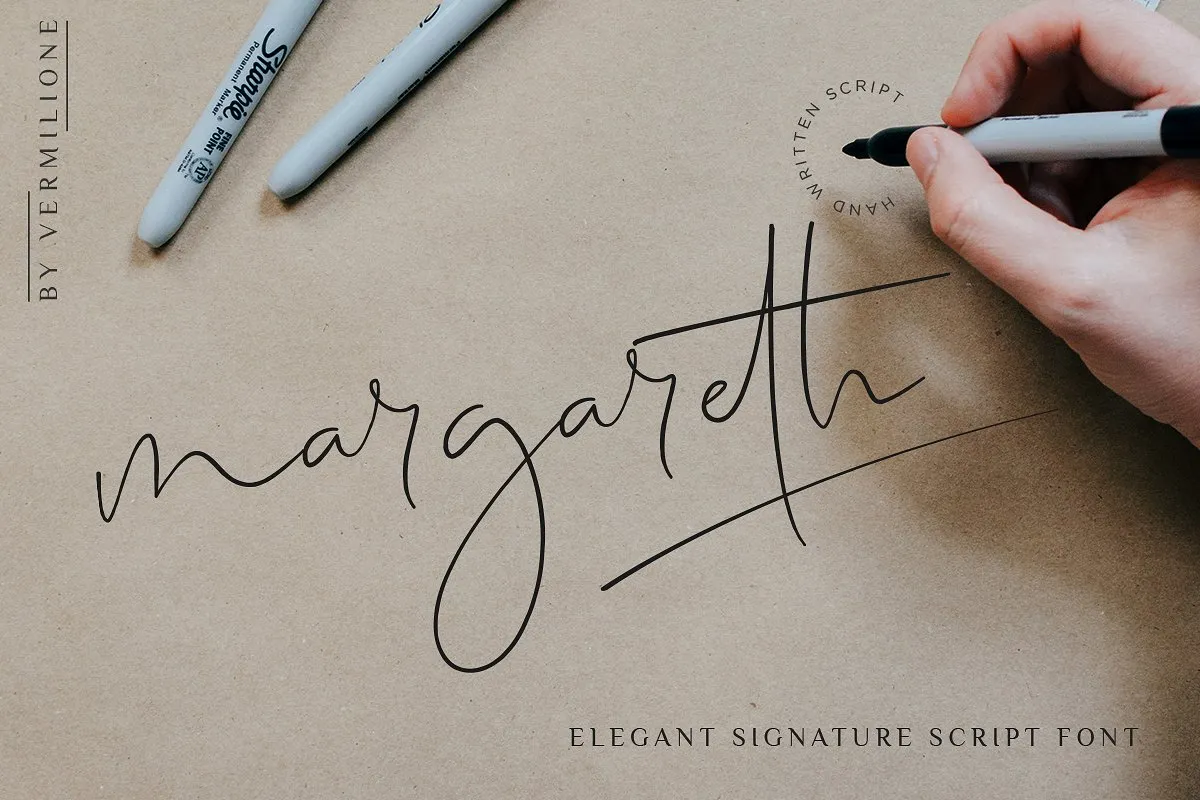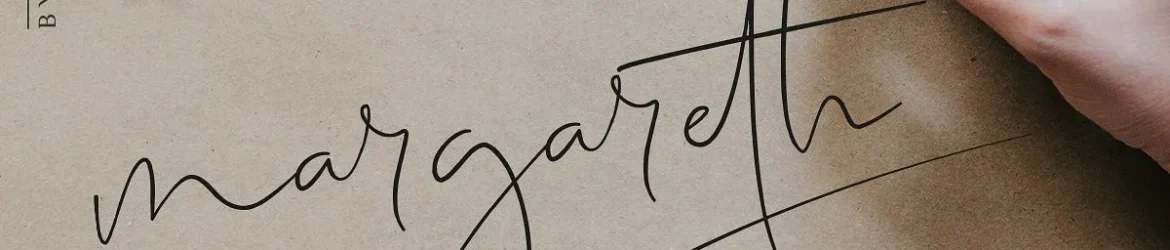
Margareth Signature Font – Download Grátis
Descubra a magia única da ‘Margareth Signature Font’ – uma elegante escrita script com estilo de letra original, que tem aparência natural e encantadora. Inspirada na autêntica escrita à mão, ela combina sutileza com simplicidade, deixando um ar feminino e sensual sem perder a facilidade de leitura. Suas letras fluíram como se fossem desenhadas por mãos delicadas, conectando-se tanto em estilos elegantes quanto simplesmente clássicos. Ideal para quem busca uma fonte que dê vida à suas criações, destacando-as com estilo único e personalidade. Através da ‘Margareth Signature Font’, você encontrará um recurso gráfico de alta qualidade, destinado a designers, criativos e aficionados em gráfica. Seja para o design de logotipos, capas de livros ou qualquer projeto que exija uma fonte única e autêntica, a ‘Margareth Signature Font’ é sua escolha perfeita. Descubra como essa elegante escrita pode tornar seus projetos ainda mais notáveis e distintivos.